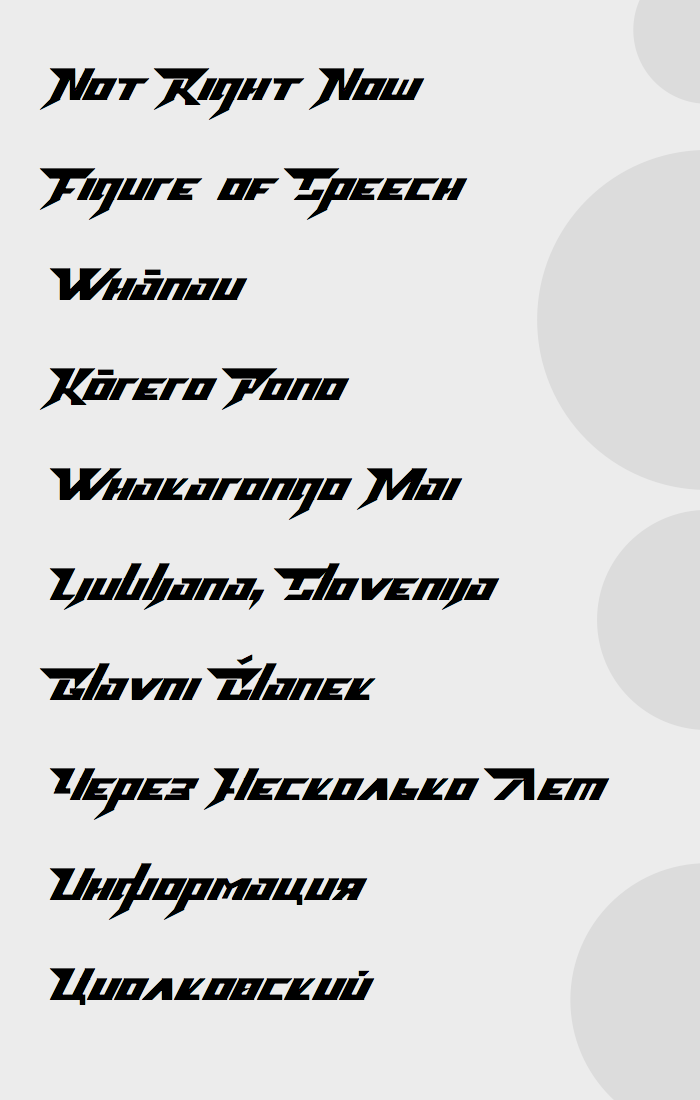
Это поросто восторг, очень круто, мне нравится. У тебя всегда отличное чувство киберпанка и футуризма (а сейчас это очень модно). А в этом шрифте ещё и восточный мотив. И огромный знаковый состав, включая гречицу и кириллицу. Моё почтение и восхищение. Я бы, может быть, сделал более острые или загнутые хвосты у Ц, Щ и б.
Спасибо большое! Вообще-то, я не имел восточный мотив в виду делая этот шрифт, но пусть говорят, что я так имел в виду, чтобы я казался умнее ))